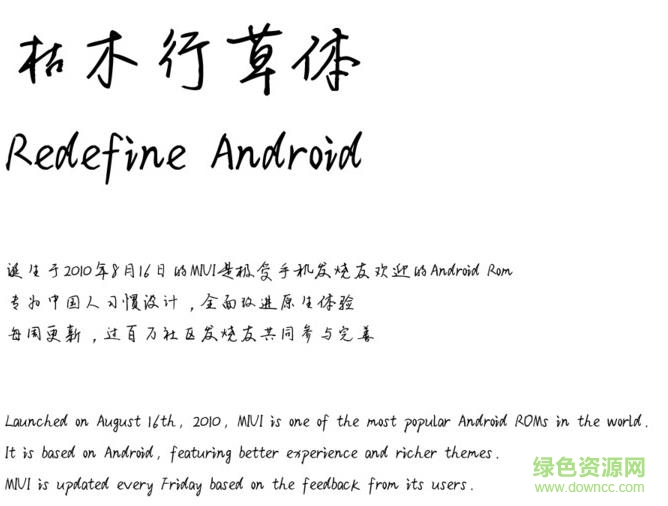
枯木行草体这款字体的使用将让你感受和到十分鲜活的气息,能够实现字体样式的枯木逢春效果,让你感受到极致享受的字体使用体验,是95后的小伙伴们打造的一款精美字体!
枯木逢春犹再发,人无两度再少年。简介:该字体出自95后小鲜肉,字体老练程度与颜值严重不符,不要以为少年就与成熟稳重绝缘,见字如见人,字形稳健雄伟、独具匠心。少年强则国强!
能够让人一见倾心,这款字体十分不错的,给你在不同场所都能够获得最佳的视觉效果!